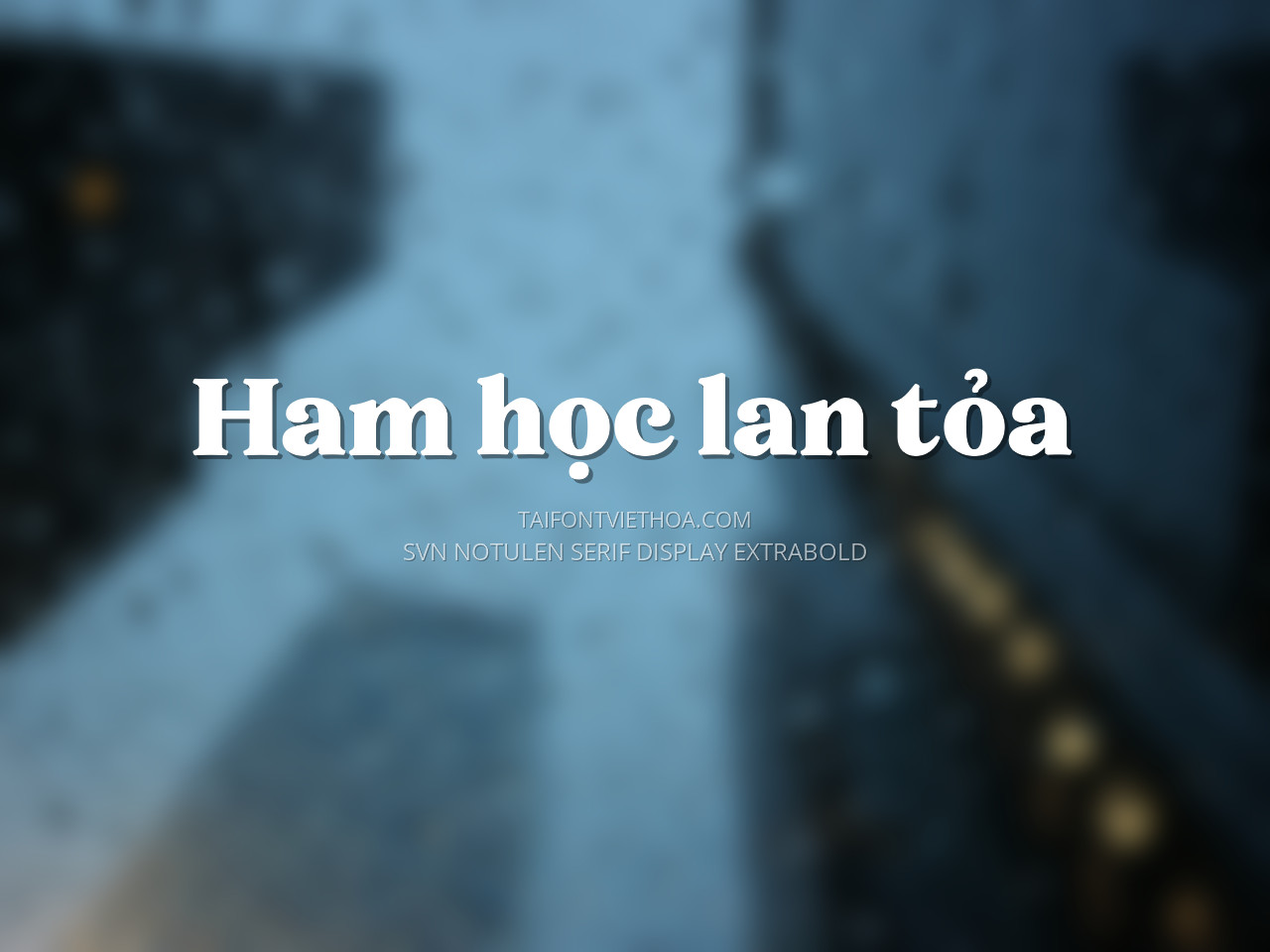
Font việt hóa SVN Notulen Serif Display Extrabold
Giới thiệu về font SVN Notulen Serif Display Extrabold – Kiểu chữ serif đậm nét, sang trọng và hiện đại
SVN Notulen Serif Display Extrabold là phiên bản Việt hóa của font Notulen – một kiểu chữ serif display với thiết kế đậm nét, tinh tế và đầy cá tính. Phiên bản Extrabold của Notulen mang lại sự mạnh mẽ, nổi bật trong từng ký tự, giúp các nhà thiết kế tạo điểm nhấn ấn tượng cho các dự án thương hiệu và truyền thông.
Phiên bản Việt hóa được Taifontviethoa.comhoàn thiện kỹ lưỡng, hỗ trợ đầy đủ dấu tiếng Việt cùng hơn 80 ngôn ngữ khác, giúp font dễ dàng ứng dụng trong các thiết kế cần sự sang trọng, nổi bật nhưng vẫn giữ được tính chuyên nghiệp và hiện đại.
Thiết kế serif đậm nét – Ứng dụng lý tưởng cho tiêu đề và nhận diện thương hiệu
SVN Notulen Serif Display Extrabold sở hữu các nét chữ dày, rõ ràng với độ tương phản cao, tạo cảm giác mạnh mẽ và cá tính. Font có cấu trúc serif truyền thống nhưng được tối ưu hóa cho các thiết kế display, giúp tăng khả năng thu hút và tạo điểm nhấn. Phong cách này rất phù hợp cho tiêu đề, poster, logo và các ấn phẩm quảng cáo cần sự nổi bật.
Ứng dụng lý tưởng: tiêu đề tạp chí, poster quảng cáo, logo thương hiệu, bao bì sản phẩm, bìa sách nghệ thuật và các dự án truyền thông cao cấp. Ngành nghề phù hợp: thời trang, mỹ phẩm, nội thất, nghệ thuật, truyền thông và các thương hiệu định vị theo phong cách sang trọng, hiện đại.